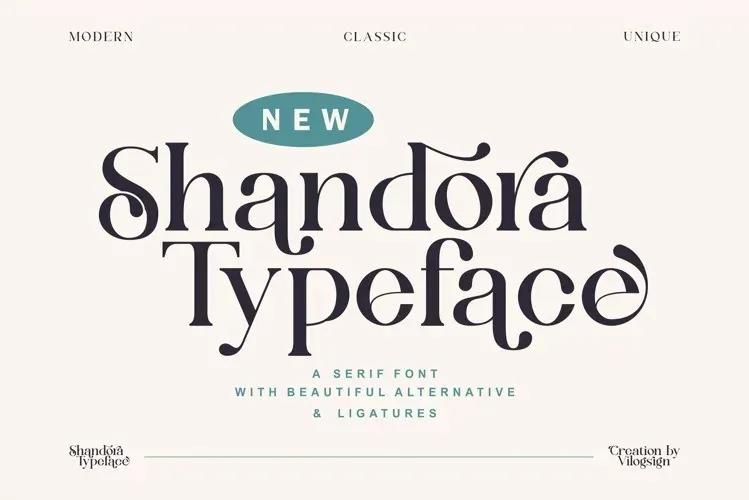
Shandora Font
A Shandora Font é uma elegante serif que traz design contemporâneo às suas criações digitais. Suas linhas suaves e modernas complementam qualquer projeto visual, tornando-o atraente, sofisticado e luxuoso. Para garantir sua unicidade e beleza única, o designer 99designs inclui alternativas altamente personalizáveis. Esta fonte se destaca não apenas pela sua qualidade excepcional para múltiplos idiomas, mas também por ser ideal para aplicativos variados como branding, cartões de convite, publicações, moda, citações, logotipos e embalagens. Sua versão multilíngue a torna perfeita para projetos internacionais que exigem uma aparência elegante em várias línguas. Uma fonte como a Shandora é fundamental para quem busca estilos sofisticados que possam marcar seu trabalho de maneira única e profissional, seja para uso pessoal ou comercial.